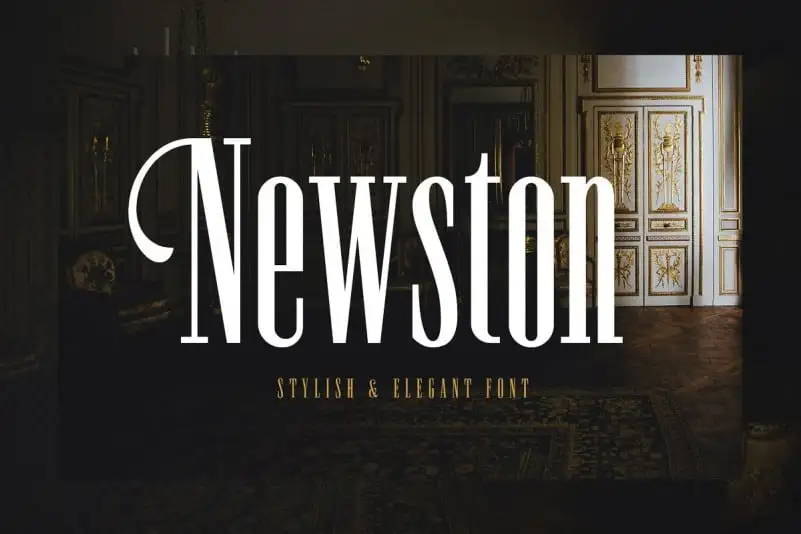
Newston Slab Serif Font – Download Grátis
Nova fonte Newston Slab Serif é uma tipografia slab serif geométrica baseada no popular Isidora e inspirada nos famosos tipos de linhas grossas do início do século XX. Essa fonte é ideal para designers que valorizam estilos modernos e clássicos, permitindo a criação de headlines impactantes graças ao forte contraste dos traços. Além disso, o espaçamento bem ajustado permite um melhor uso da página, adaptando-se perfeitamente para projetos typográficos contemporâneos ou mais tradicionais. Com quatro estilos disponíveis, Newston Slab Serif oferece uma versatilidade que vai desde o elegante e minimalista até o robusto e vibrante. Sua qualidade e diversidade garantem uma adição valiosa aos seus projetos gráficos.